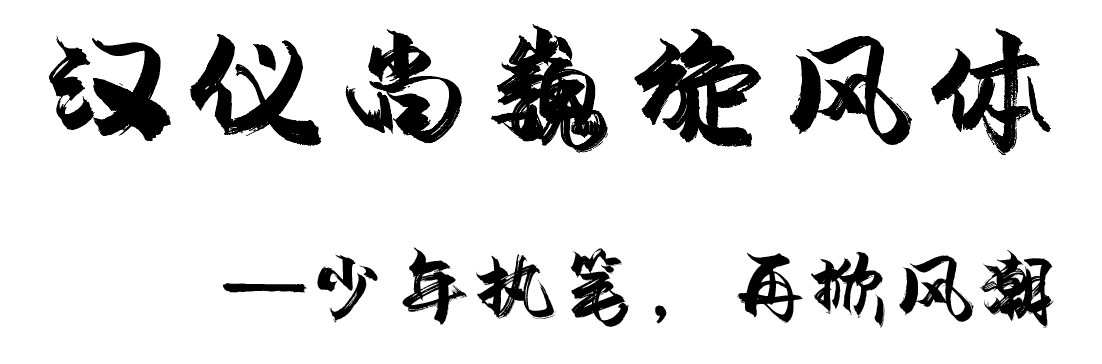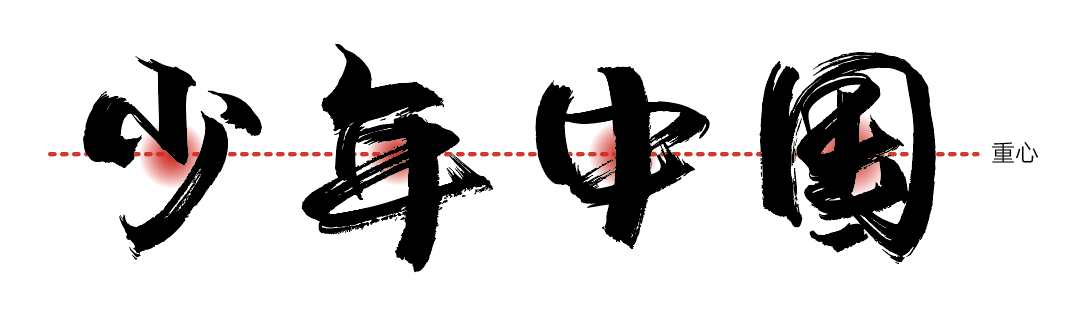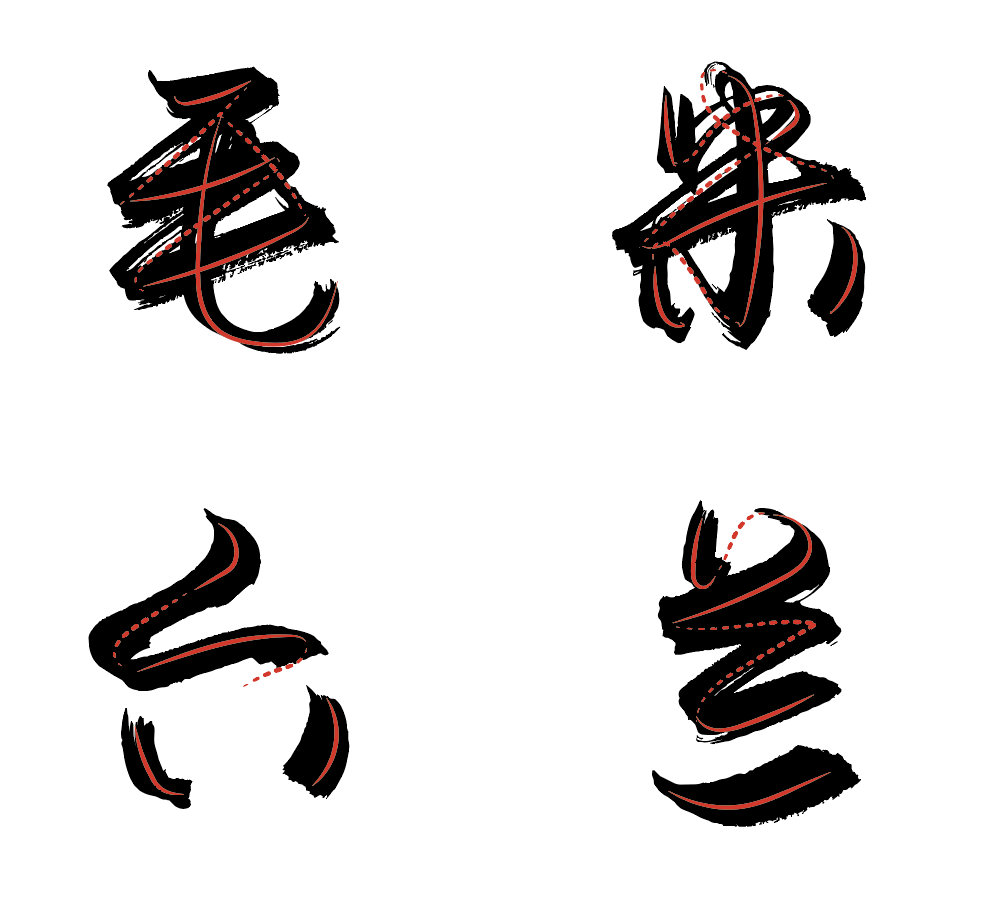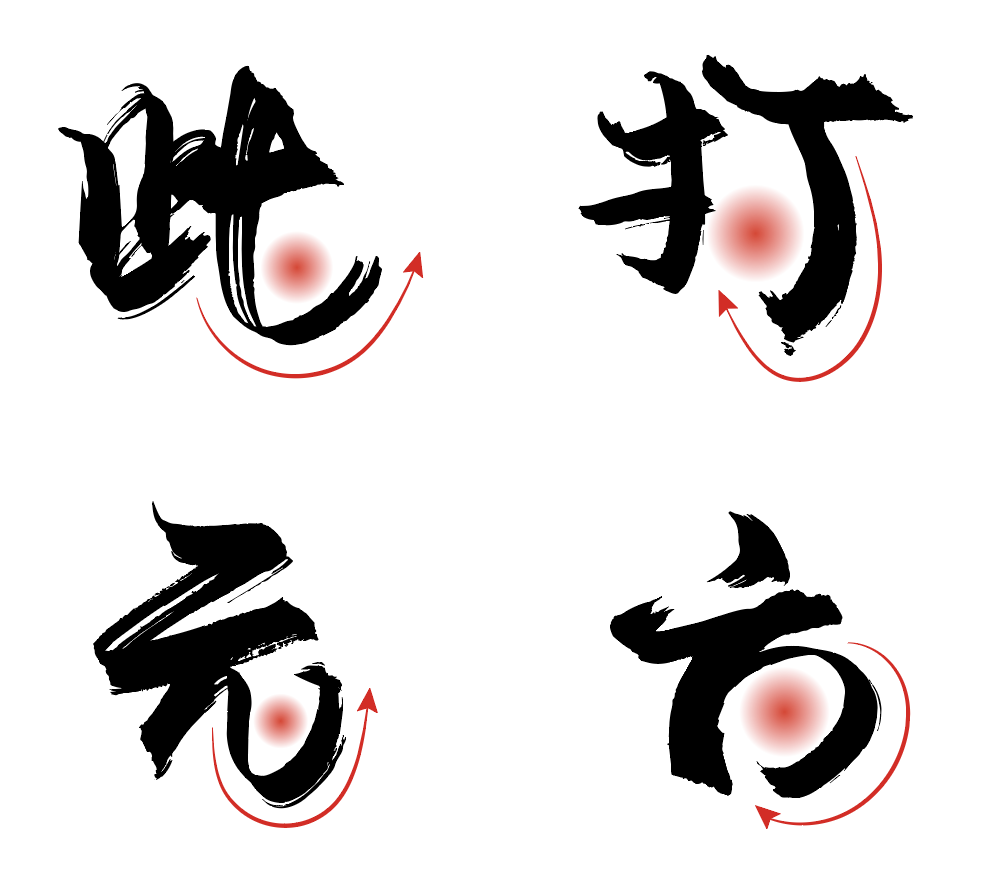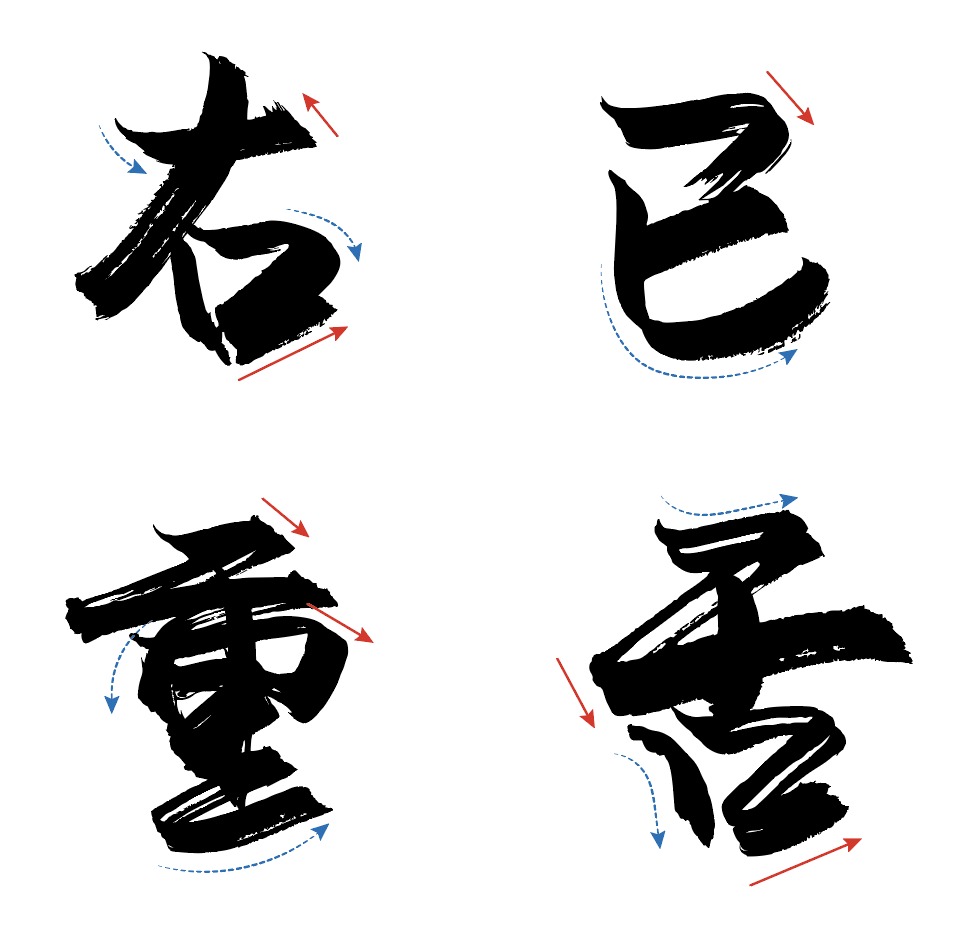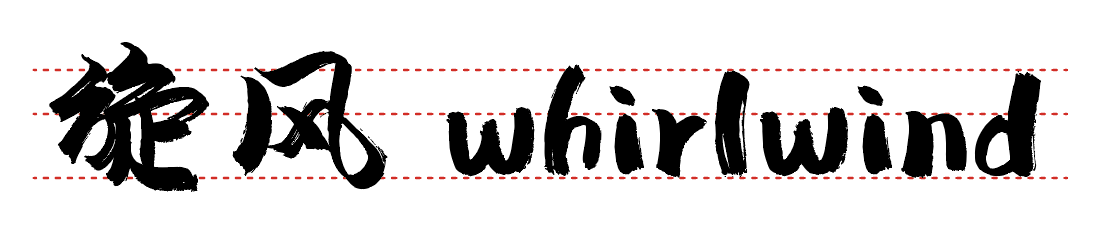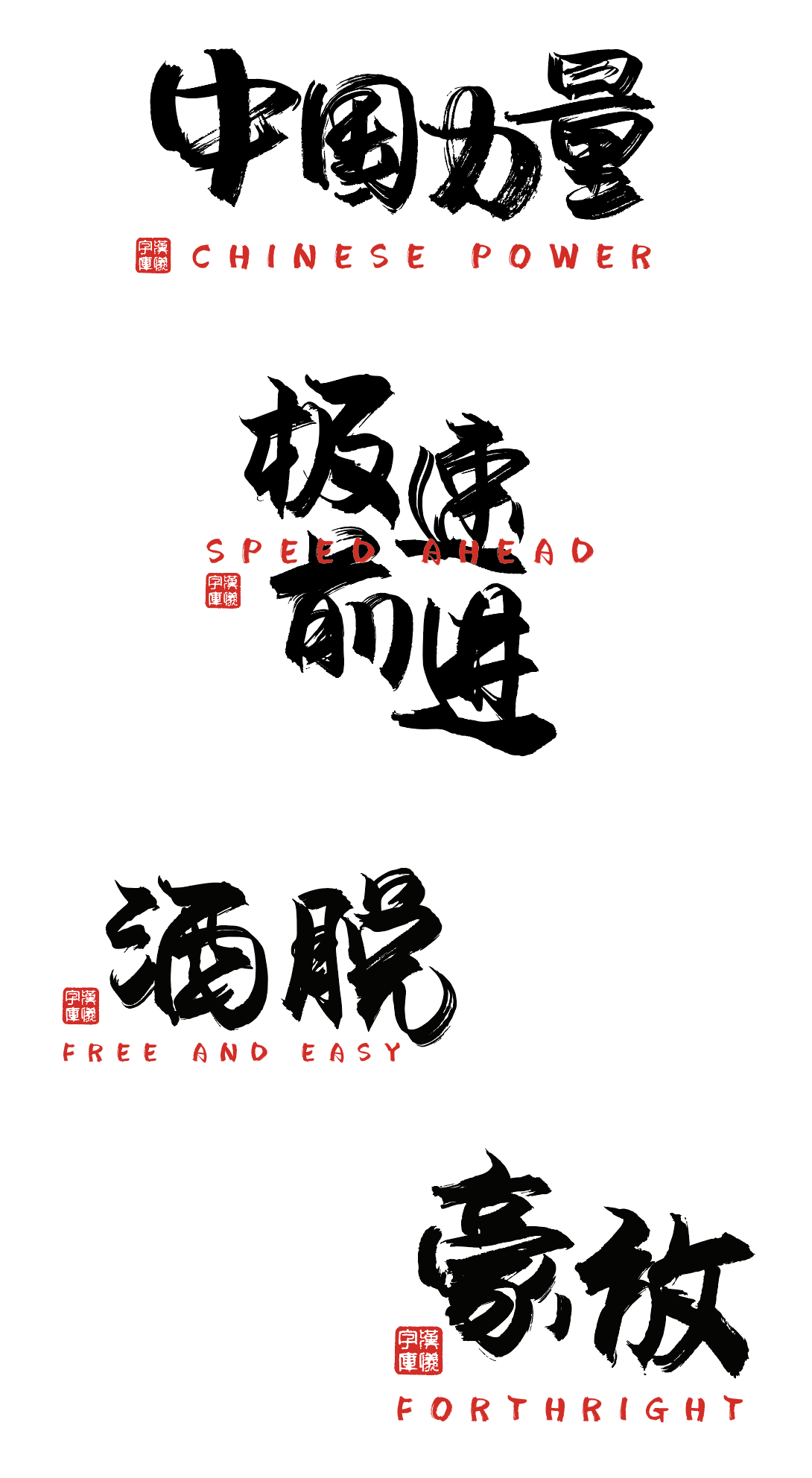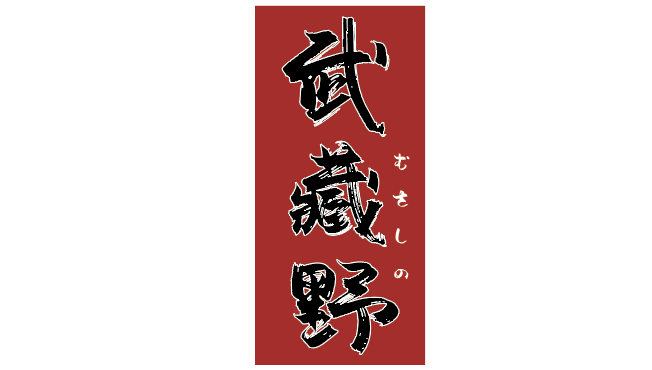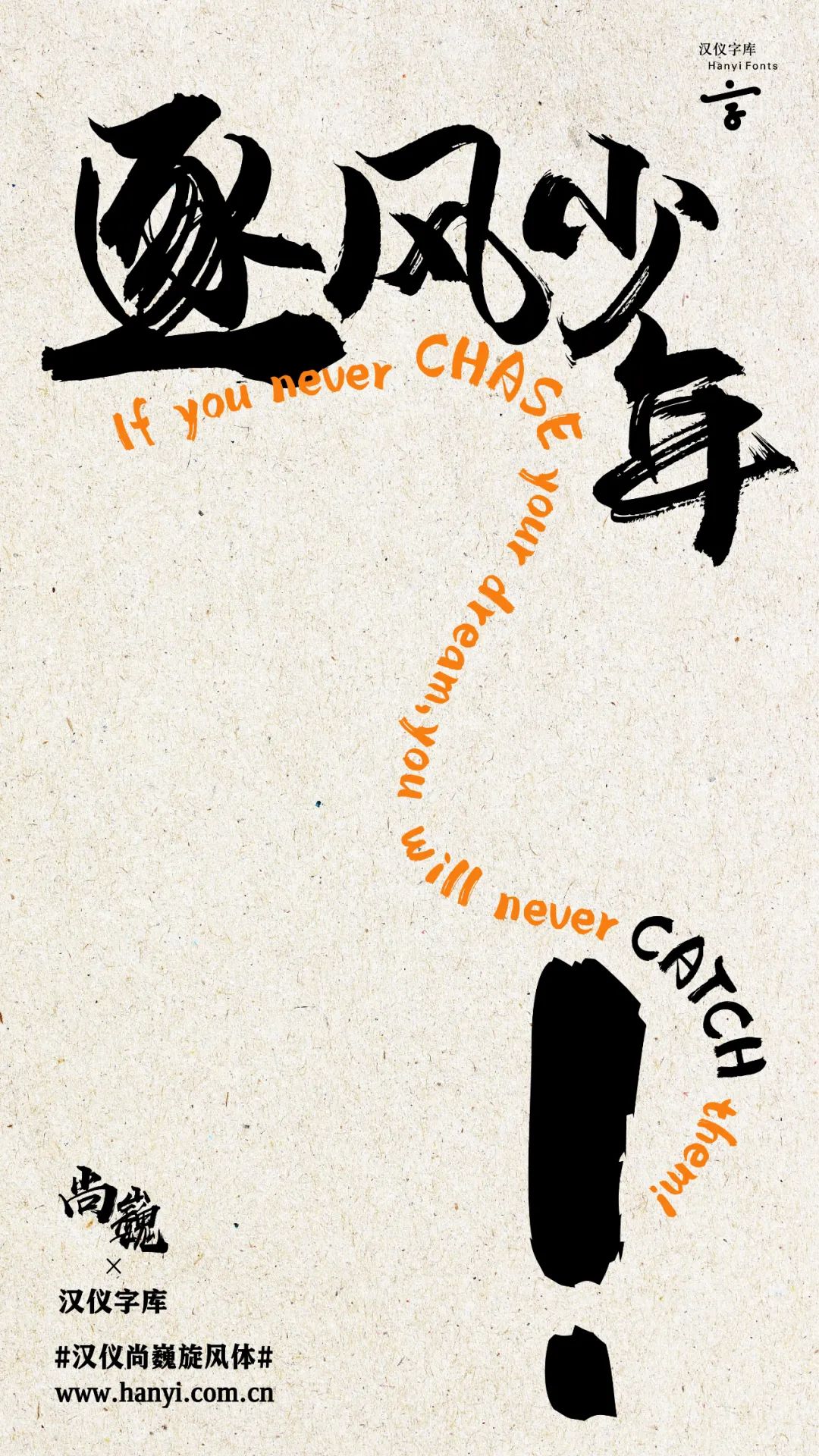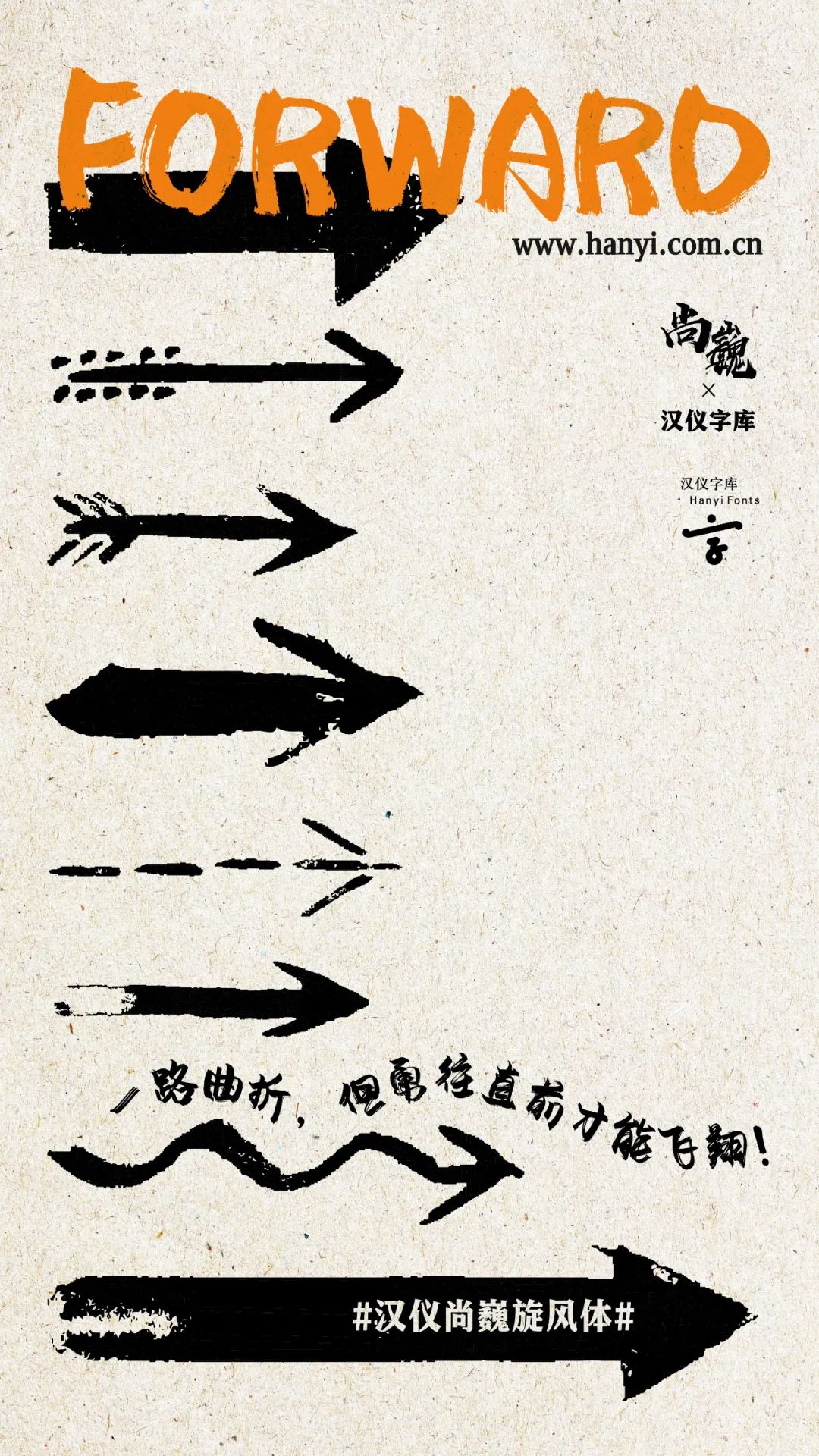
汉仪尚巍旋风体字体介绍,汉仪尚巍旋风体字体设计灵感
汉仪尚巍旋风体 | 背景介绍
汉仪尚巍旋风体出自汉仪字库签约设计师尚巍。他是一个行走于机打时代的手写人、跨界设计师、美学创意人、书法创作人;他是一位90后,却花了20年的时间不断诠释他对书法的情怀;他在这个浮躁的年代,坚持着自己的手写风格,不骄不躁;他被称作是一个带着传统,却敢倒立行走的新生代艺术家。
汉仪字库与尚巍已合作开发出多款热门字体,这款汉仪尚巍旋风体的风格潇洒豪放,将传统的书法文化与现代的时尚潮流融为一体,适用于游戏页面或中国风电影海报等众多商业场合。
汉仪尚巍旋风体 | 字形特点
汉仪尚巍旋风体是一款潇洒自如、如风般疾速酷炫的字体。虽然名为“旋风”,但笔画粗细均衡,重心稳定,字形气势整齐统一。
汉仪尚巍旋风体 | 笔画特点
汉仪尚巍旋风体的笔画有着很强的连贯性,手写的飞白效果使字体的气息更加流畅,笔画间的关系密不可分,同时也增加了字体的速度感和放浪不羁之感。
汉仪尚巍旋风体的笔画豪放,字迹飞扬。字体空间即饱满又有弹性,展现了设计师的浑厚功底。
汉仪尚巍旋风体的笔画线条充满韧劲。字体曲中带刚,遒劲有力,松弛有度,毫不吝啬的展现了手写字体的生动与魅力,表现了字体的力量感与速度感。
汉仪尚巍旋风体 | 中西文匹配
汉仪尚巍旋风体的西文同样用毛笔书写,融入了中文书法的手写方式。笔触丰富,运笔流畅,手写感强,给予了线条更多的变化,弹性十足。
汉仪尚巍旋风体 | 排版效果
汉仪尚巍旋风体 | 海报展示